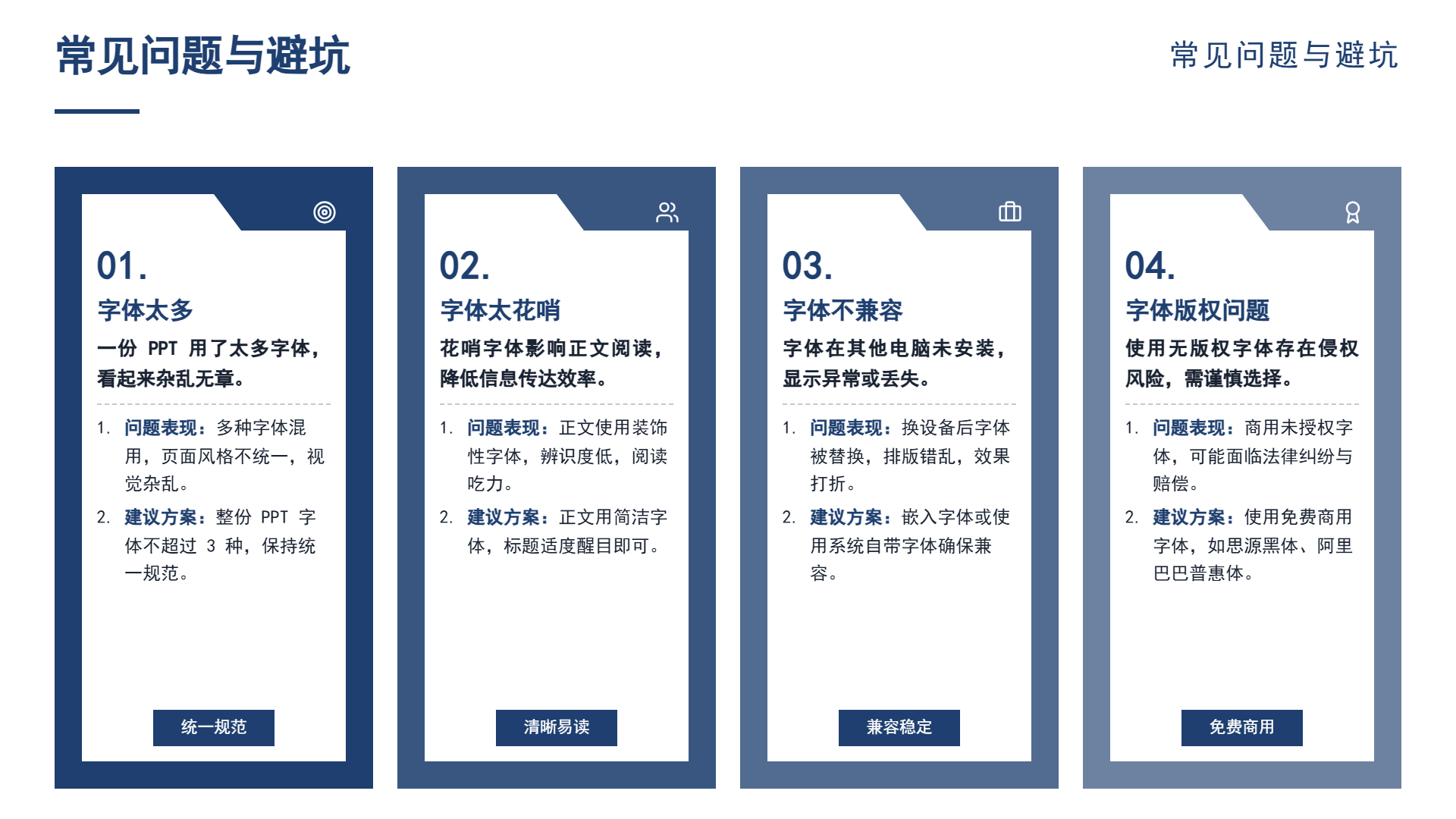
ppt字体,决定了整体的质感,字体选对了, PPT看上去专业,高端。字写得不好,总体显得低廉。
文章讲PPT字体如何选才不会显得低廉。
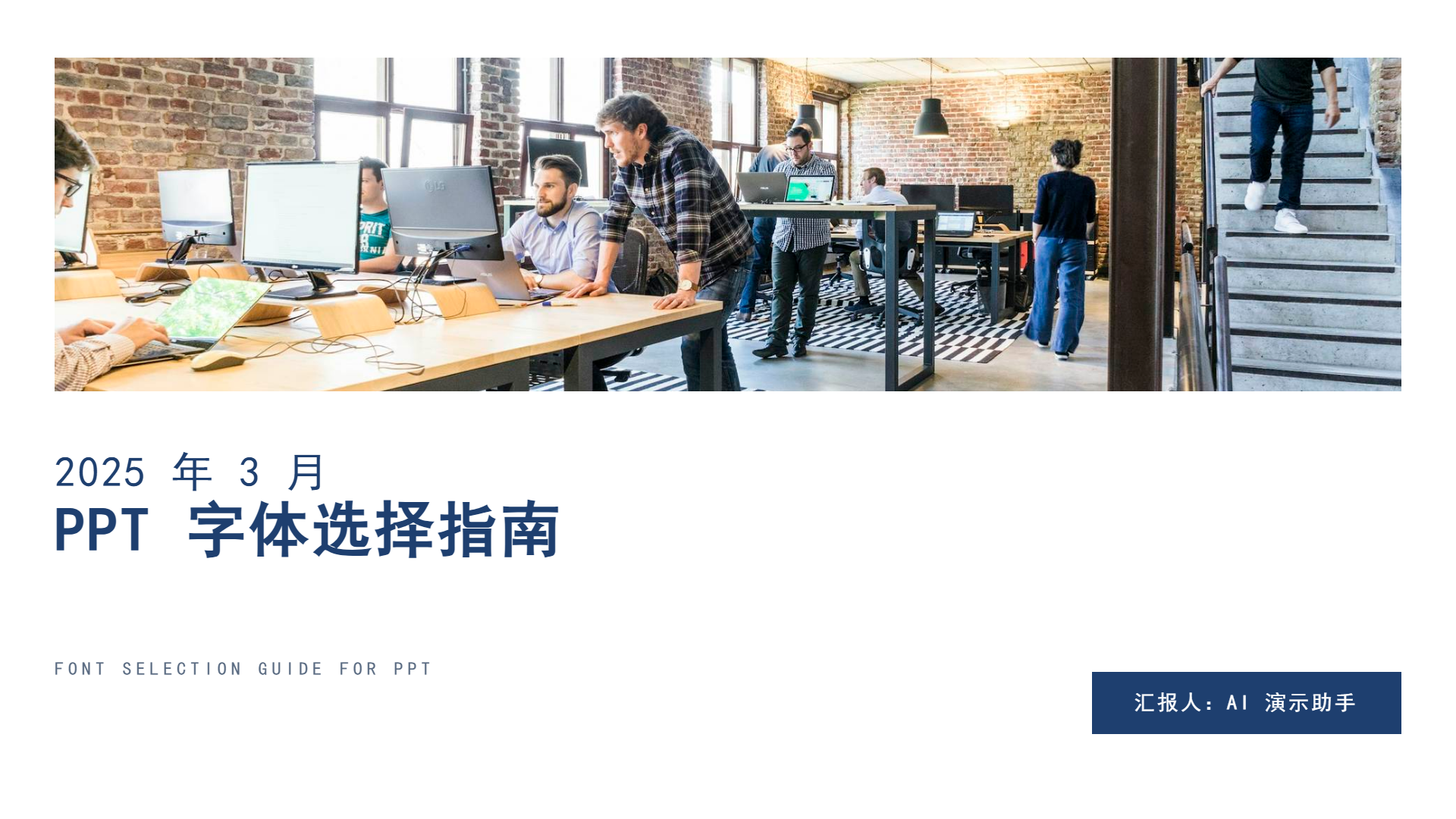
PPT 字体的核心原则
PPT字体的基本原则,并非“字体多”,而是“统一规则”。
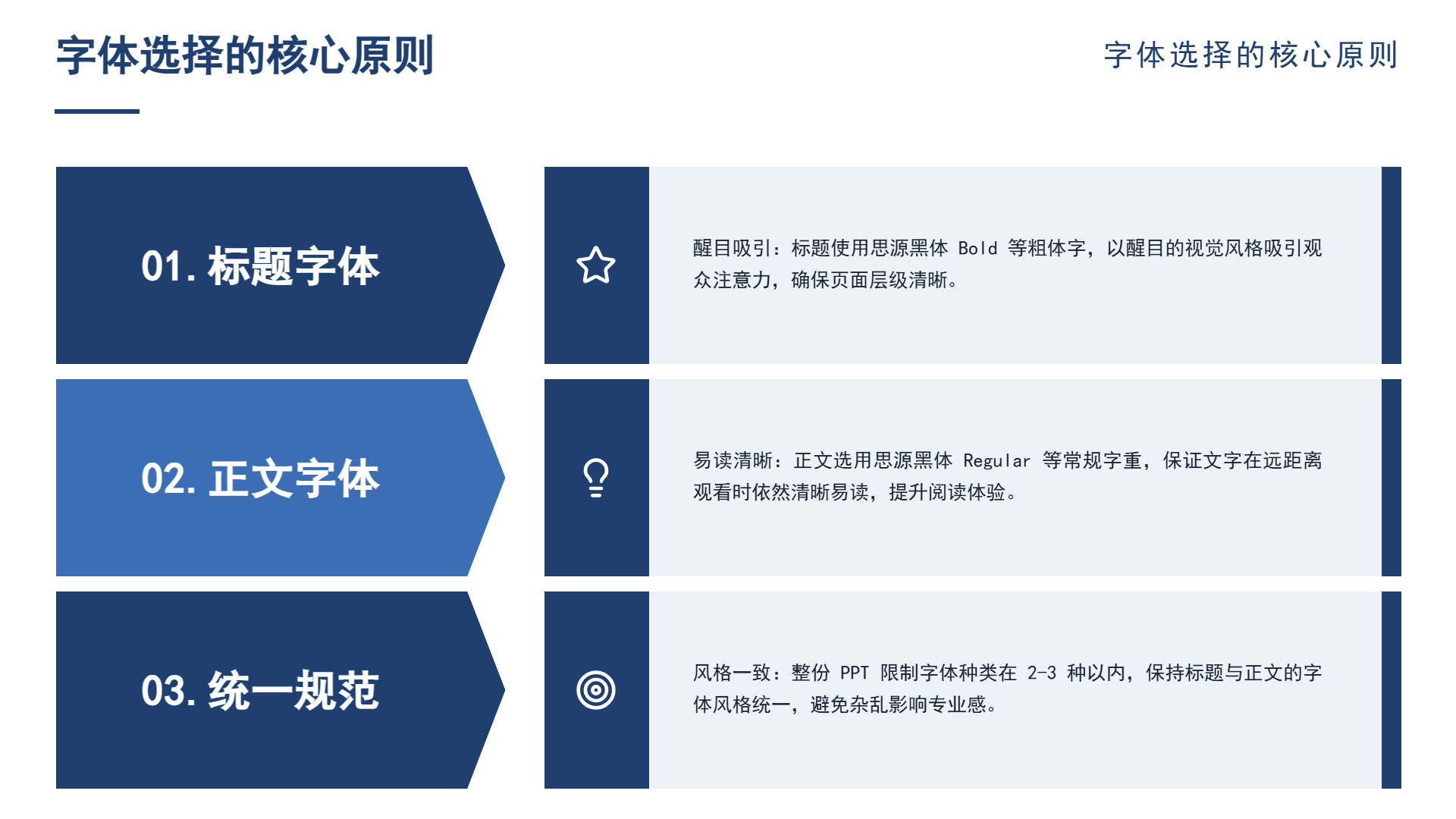
一个PPT字体不用太多, 2 ~ 3种就可以了,具体说来, PPT字写得遵循三条原则:标题字,正文字,统一规则。
标题的字体:标题使用醒目字体,引起观众的注意,正文文字:正文以易读字体为主。统一标准:整个PPT字体一致,风格一致。
PPT 字体推荐
PPT字体推荐使用下面几种方式。
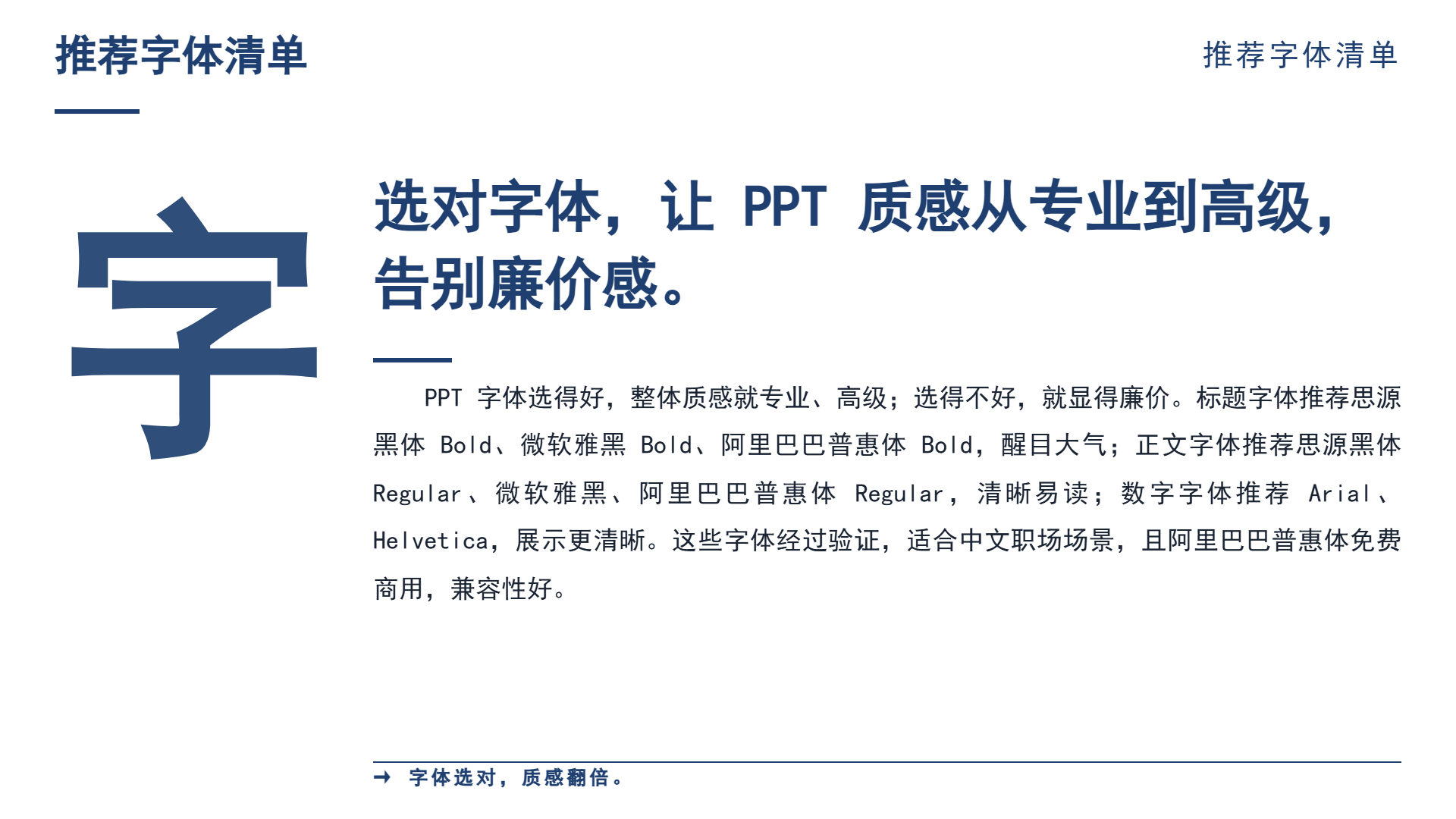
标题的字体:思源黑ld,微软的雅黑Bold,阿里的普惠体bold。这几个字体显眼大方,适合题目。正文的字体有思源黑的Regular,微软的雅黑,阿里的普惠体的regular,这些字清晰易懂,适合正篇。数字的字体: Aral, Helvetica,这些字在数字上显得更清楚。
PPT 字体的常见问题
PPT字体存在一些常见的问题,避开就成功一半了。
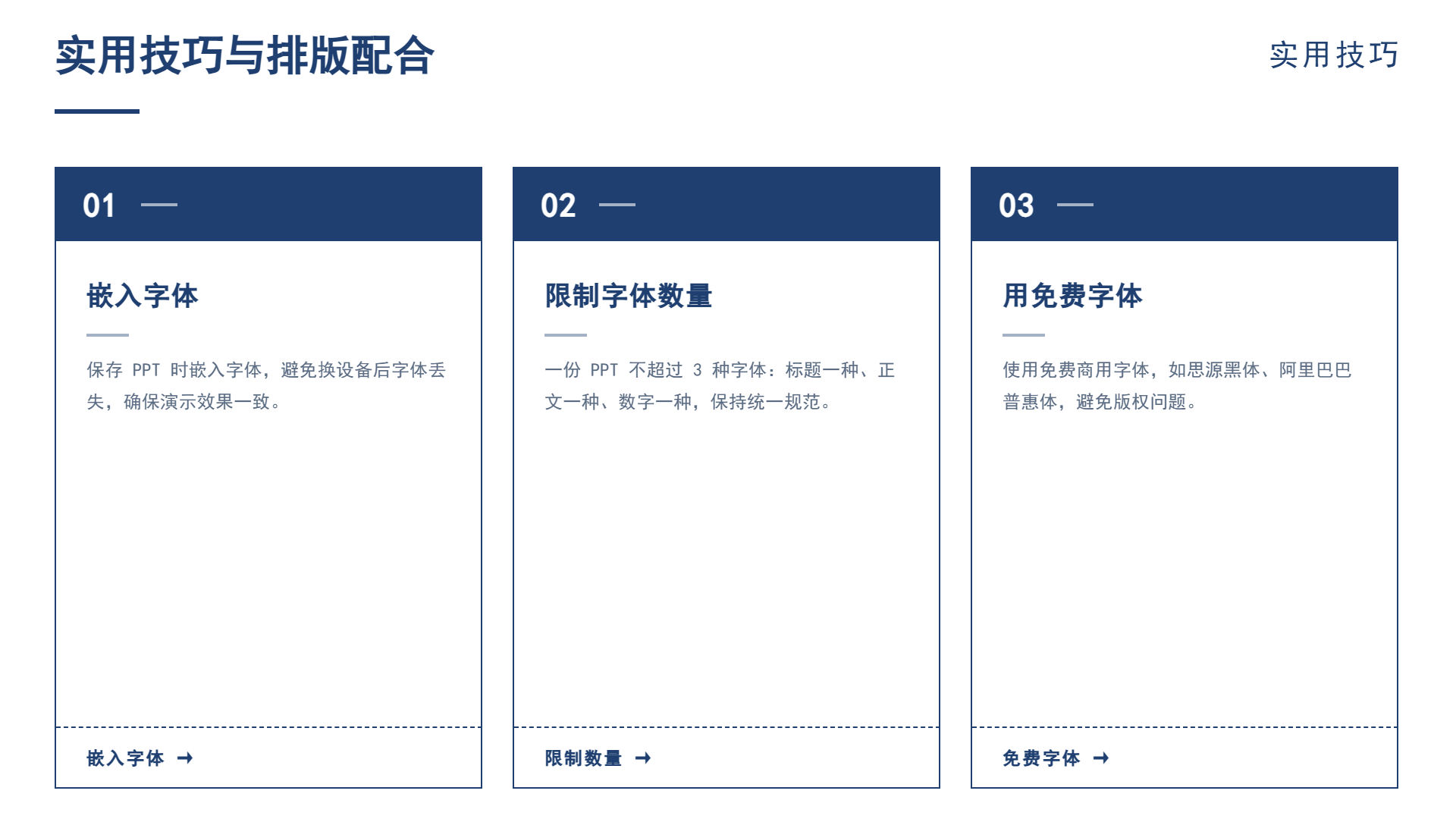
问题之一:字太多,一个PPT使用太多的字体,显得杂乱无章。问题之一:字体过于花哨,使用了太多花哨字体,正文不易读懂。问题二:字体无法兼容,字体其它电脑未安装,显示异样。问题之四:字体的版权方面的问题。使用无版权字体,有侵权危险。
PPT 字体的实用技巧
PPT字体几个常用技巧,使用好效果提升。
第一嵌字体。在保存PPT的时候,将字体嵌入到其中,以免更换设备之后字体被丢失第二,减少字体的数量,一个PPT不得超过3个字体,标题一个正文一个数字一个。第三,用免费的字体,免费使用商用字,防止版权纠纷。第四,用系统的字体。用自带字体的话,兼容性比较好。
字体与排版的关系
字体与排版结合使用,效果更佳。
字体的大小要适中,标题为28 ~ 36号,正文为14 ~ 20号,行距合适正文的行距一般为1. 5。字的间距要适中,不要太大,也不要过紧,字的颜色与背景要相互对比,保证清晰可阅。
- PPT字体怎么选才不显得廉价?
遵循标题字体醒目、正文字体易读、全篇统一的原则,推荐使用思源黑体、微软雅黑等安全字体,避免过多或花哨字体。
- PPT中应该使用几种字体?
建议不超过3种:标题一种、正文一种、数字一种,保持整体风格统一。
- PPT字体常见问题有哪些?
字体过多显得杂乱、花哨字体不易读、未安装字体导致显示异常、使用有版权字体可能侵权。
- 如何避免字体在其他电脑上丢失?
在保存PPT时选择嵌入字体,或使用系统自带字体提高兼容性。